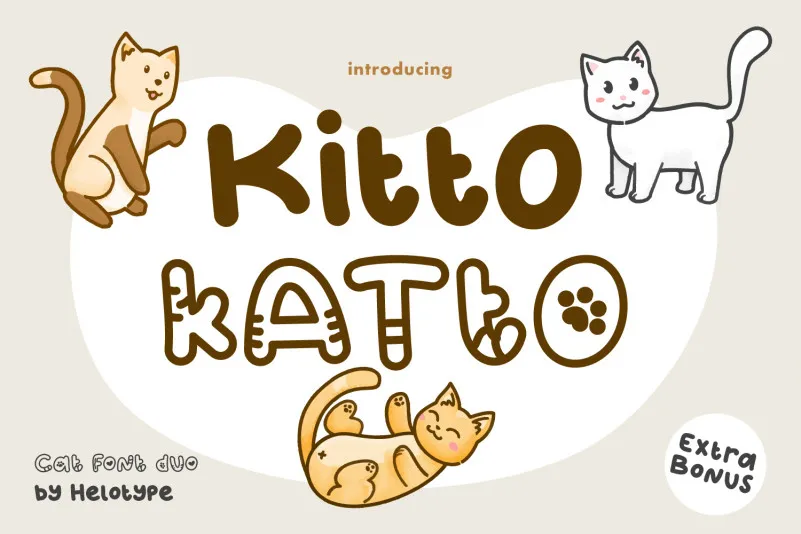
A fonte Kitto Regular é uma escolha perfeita para qualquer projeto infantojuvenil ou educacional, oferecendo um toque divertido e autêntico que cativa a atenção dos pequenos mentes ainda frescas e curiosas. Seu design simpático e carinhoso faz deste fonte uma opção ideal para atividades lúdicas em salas de aula ou projetos escolares, onde o elemento criativo e alegre pode inspirar tanto professores quanto estudantes. Com seu charme encantador, Kitto Regular oferece uma maneira única de trazer um pouco mais de vida e diversão para qualquer projeto que você possa estar desenvolvendo, tornando-a não apenas uma escolha estética, mas também uma opção educacional inspiradora. Seja em um trabalho de sala de aula ou até mesmo no seu próximo artesanato infantil, Kitto Regular é certamente um recurso gráfico indispensável.